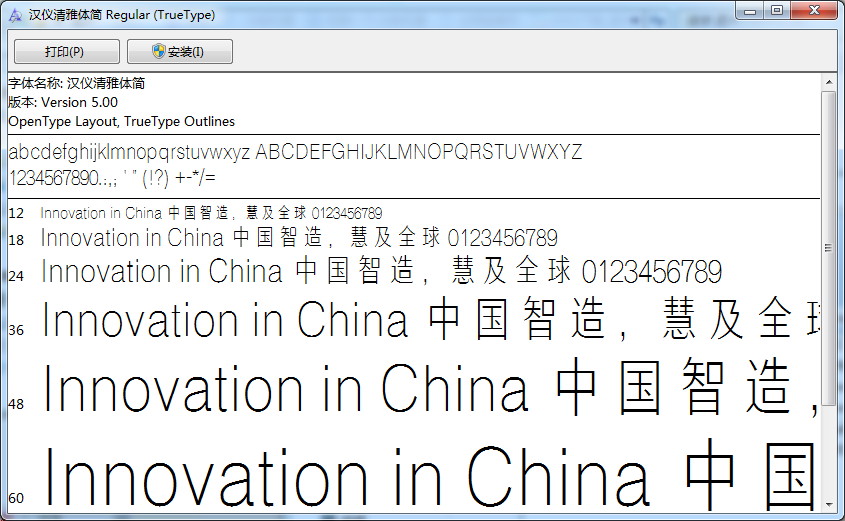
hyqingyatij字體也叫漢儀清雅體,是一款清麗優(yōu)美的字體,線條筆直而不呆板,具有一種自然的美,經(jīng)典耐看,用在哪里都不跌份,歡迎大家免費(fèi)下載!
現(xiàn)代字體設(shè)計趨于清晰簡潔,為迎合現(xiàn)代特征,字體設(shè)計被簡化,襯線逐漸被去除,線條也不再有粗細(xì)之分,干凈利落,更具機(jī)械繪制的特點(diǎn)。